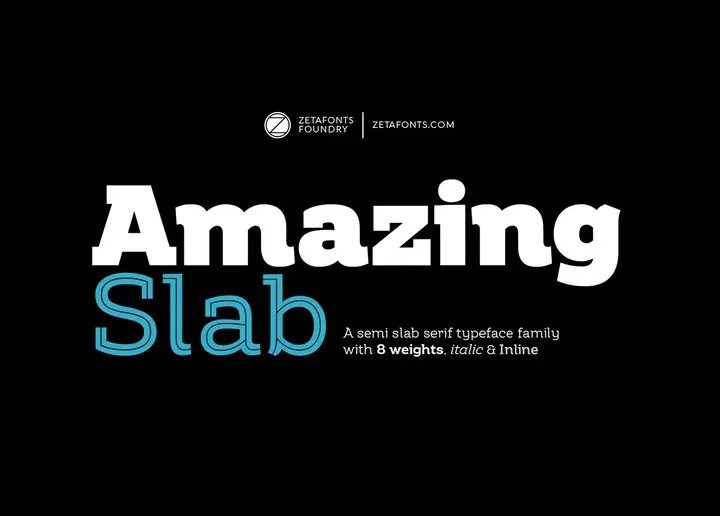
Esta é uma família de fontes slab serif limpa e contemporânea projetada por Francesco Canovaro e Andrea Tartarelli como evolução do famoso Amazing Grotesk, desenvolvido por Cosimo Lorenzo Pancini. Sua influência vem da robusta personalidade das letras extra-bonitas do logo StartupItalia de Canovaro, que informam os pesos de exibição mais pesados (de média até preto). Cada um desses pesos foi combinado com uma versão inline projetada por Mario De Libero, para expandir o uso desta família de fontes desde sinalização em destaque até criação de logotipos e titulação editorial. A combinação única entre estilos humanistas, serifas egípcias e linhas retas confere ao texto um toque dinâmico e simpático que transmite uma ideia de inovação, informação e energia, com uma paixão pela simplificação direta da comunicação. É uma escolha perfeita para quem procura expressar a essência vibrante do ecossistema startup no seu design.